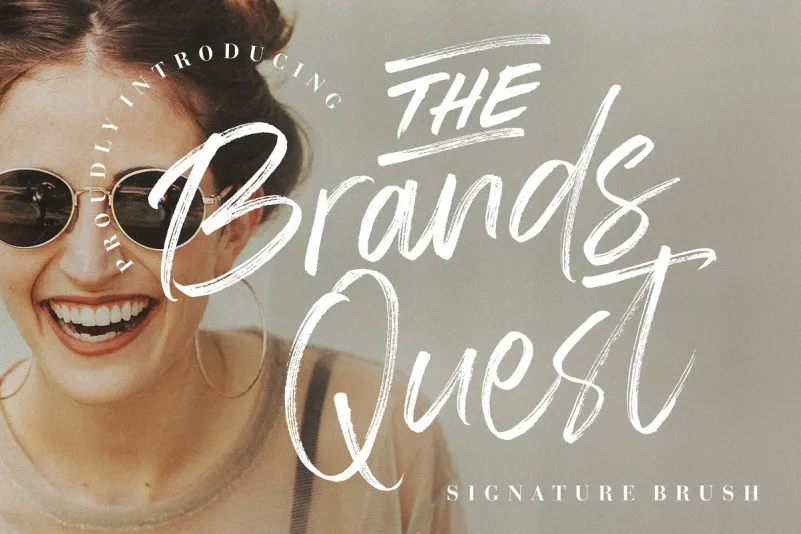
The Brands Quest Font – Fonte Grátis
The Brands Quest Font
A fonte “The Brands Quest” é uma escolha perfeita para designers que buscam uma solução clara e confortável para qualquer projeto visual. Ela se assemelha a um traço de pincel, mas não é complexo; ao contrário, proporciona um leque vasto de possibilidades sem comprometer sua simplicidade. Esta fonte atinge o nível mais alto em várias tarefas de design, como projetos de marca, logotipos, designs de casamentos, postagens no Instagram, anúncios e embalagens de produtos. Também é perfeita para trabalhos que exigem um sabor autêntico da escrita a mão, sejam eles em camisetas personalizadas, fotos de produto ou até mesmo em cartões de visita. Seja você criando uma nova marca, desenvolvendo embalagens sofisticadas ou apenas enviando postagens no Instagram que precisam ser únicas e envolventes, “The Brands Quest” vai te levantar a um novo nível. Seja qual for o projeto, esse script font será a escolha certa para dar vida ao seu design de uma maneira única e perfeita para transmitir sua marca de forma autêntica e cativante.